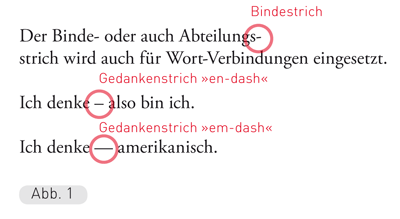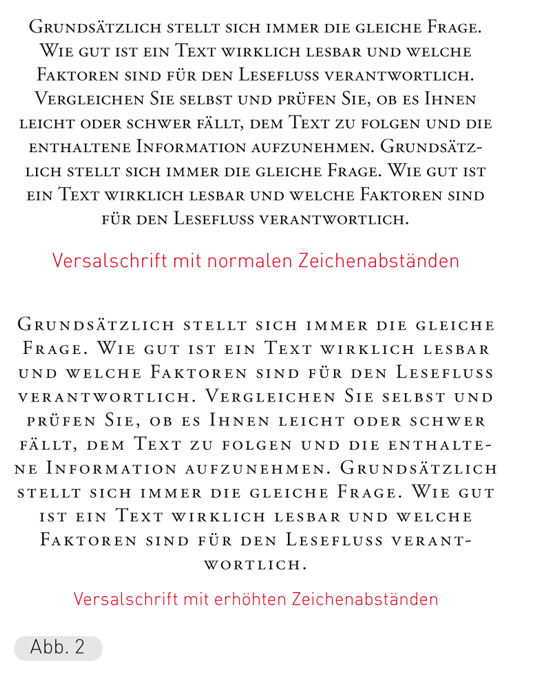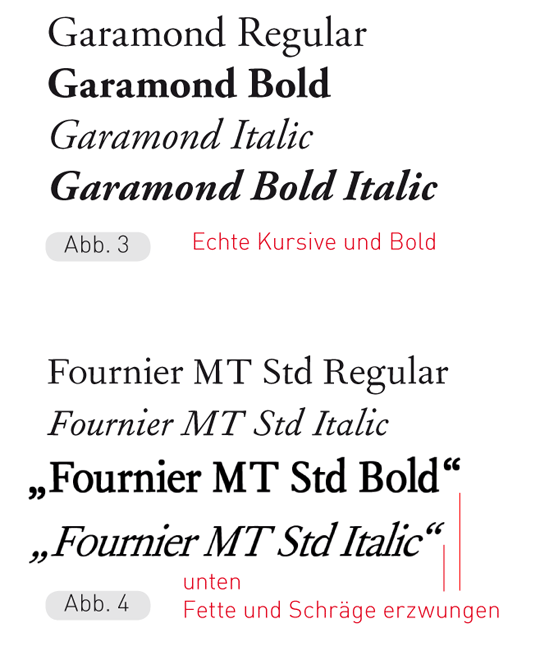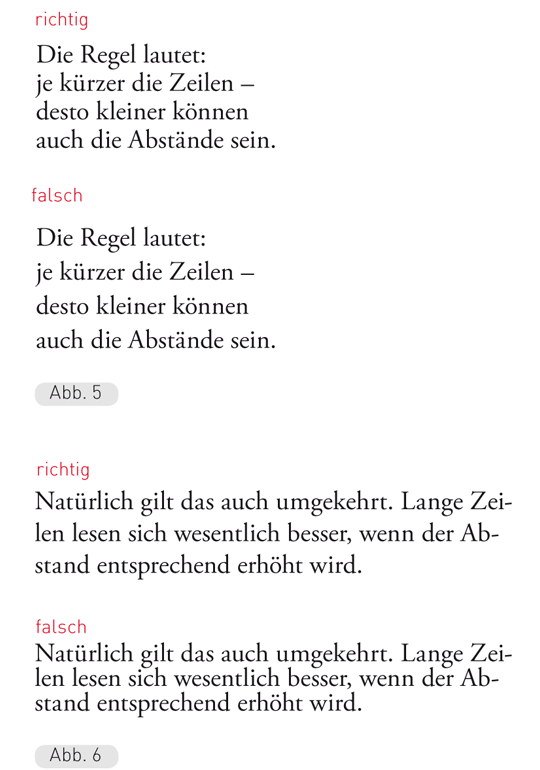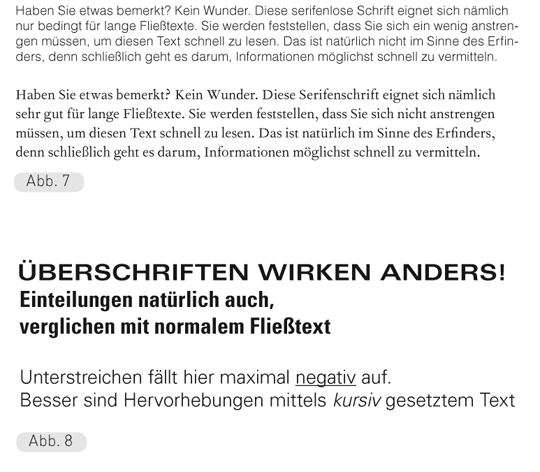
…Einfach einen Text setzen, ein Bild hinzufügen und ein wenig mit den Parametern herumspielen reicht – wie Sie wissen – nämlich nicht aus, um saubere und vor allem effektive Layouts vorweisen zu können. Damit Ihre Arbeiten künftig noch besser und schöner werden, finden Sie hier die wichtigsten Anhaltspunkte in den sogenannten Goldenen Regeln, sprich die wichtigsten Regeln der Typografie. Dabei handelt es sich oft um banale Kleinigkeiten, deren Nichtbeachtung gravierende Auswirkungen auf das Erscheinungsbild Ihrer Arbeit haben können. Sie haben sich im Laufe der Jahrhunderte herausgebildet und begründen sich auf der Leseerfahrung von Millionen und Abermillionen von Lesern. Dennoch sollten die folgenden Ratschläge als solche verstanden werden und Ihnen keinesfalls die Freude am Experimentieren nehmen!
Satzzeichen und Leerzeichen
Jedem Satzzeichen folgt ein Leerzeichen!
Der Fachbegriff für die Satzzeichen (besser: Gliederungszeichen) ist Interpunktionen. Dies ist der allgemeine Sammelbegriff für Punkt, Beistrich (das Komma), Strichpunkt (das Semikolon), Doppelpunkt (das Kolon), Bindestrich (das Divis), Gedankenstrich, Fragezeichen, Ausrufezeichen, runde Klammer (die Parenthese), eckige Klammer, Auslassungszeichen (der Apostroph) und die diversen Anführungszeichen. Das et-Zeichen (&) ist eigentlich eine Ligatur und zählt nicht zu den Interpunktionen. Auch Paragraph, Kreuz und Stern gelten als Zeichen und nicht als Interpunktionen. Jedem Satzzeichen folgt zwar ein Leerzeichen, aber es gibt Ausnahmen wie z.B. bei Bindestrich, Klammer, Apostroph und die Anführungszeichen.
Der Grund, weshalb auf Punkt, Beistrich, Strichpunkt, Doppelpunkt, Gedankenstrich, Frage- und Ausrufungszeichen ein Leerzeichen zu folgen hat, ist ebenso leicht gefunden. Wieder einmal geht es um die Lesbarkeit – um das möglichst rasche Erfassen von Zusammenhängen oder eben Nicht-Zusammenhängen. Der Superstar unter den Zeichen – das Leerzeichen – steht, im Zusammenhang mit einem Satzzeichen, für eine logisch-sinnvolle Pause und gönnt dem Auge den Bruchteil einer Sekunde etwas Erholung.
Gedankenstriche...
Wie Sie bereits wissen, ist Querstrich in der Typografie nicht gleich Querstrich. Immer wieder passiert es, dass anstelle des Gedankenstrichs ein Bindestrich verwendet wird. Diese beiden sind keineswegs gleich. Genauer gesagt wird zwischen drei Arten des Querstriches unterschieden:
- Der Binde- oder Abteilungsstrich ist der kürzeste von den dreien und wird – wie der Name schon sagt – eingesetzt, wenn ein Wort abzuteilen ist beziehungsweise mehrere Wörter miteinander verbunden sein sollen (Abb. 1).
- Der kurze Gedankenstrich oder »endash« ist ein Halbgeviert lang und gilt als der eigentliche – allgemein bekannte Gedankenstrich. Vor und nach dem Gedankenstrich ist unbedingt ein Leerzeichen zu setzen. Dieser Gedankenstrich stellt eine kurze Pause dar oder signalisiert einen Einschub in den Text. Außerdem wird er bei der Angabe von Zeiträumen (von 1860–1996) oder auch als Bindezeichen verwendet, wenn Wegstrecken (Basel–Berlin) angegeben werden. In diesen Fällen allerdings ohne Leerzeichen.
Die Anführungszeichen
Das französische Anführungszeichen wird im Deutschen mit der Spitze zum Wort gesetzt. Die An- und Abführungszeichen stehen ohne Abstand vor beziehungsweise nach dem Wort und symbolisieren in der Regel die wörtliche Rede, während das einfache Anführungszeichen für Begriffe steht – Er sagte: »Das Wort ›Verrat‹ habe ich nie gebraucht«. Ob Sie deutsche oder französische Anführungszeichen verwenden, bleibt Ihnen überlassen. Sie müssen die einmal gewählten Zeichen allerdings im ganzen Dokument beibehalten!
Die Gänsefüßchen oder deutsche Anführungszeichen werden heute kaum noch verwendet, allenfalls bei Frakturschrift, wobei sie am Anfang unten und am Ende oben stehen. Behandelt werden sie wie die anderen Anführungszeichen.
Das Auslassungszeichen (der Apostroph) wird innerhalb eines Wortes ohne Zwischenraum gesetzt. Am Schluss mit etwas weniger Abstand zum nächsten Buchstaben als der übliche Zeichenabstand. Außerdem muss in Zeiten des Desk Top Publishing leider sogar auf den Unterschied zwischen dem Minutenzeichen und einem echten Apostroph hingewiesen werden.
Zeichenabstände
Falls Sie einen Text versal setzen sollten, haben Sie zwei Dinge besonders zu beachten. Einerseits sollten Sie einen kleineren Schriftgrad wählen, um einen optimalen Lesefluß zu gewährleisten, andererseits sollten Sie die Zeichenabstände erhöhen, da die Buchstabenabstände eine Funktion der Buchstabeninnenräume sind.
Je kleiner die Innenräume, desto kleiner auch die Abstände. Je größer die Innenräume, desto größer die Zwischenräume. Da Versalien naturgemäß größere Buchstabeninnenräume besitzen als Kleinbuchstaben, werden bei versal gesetzten Texten die Zeichenabstände logischerweise erhöht (Abb. 2).
Bold und Italic
Sie werden sich nun bestimmt fragen, warum Sie den Gebrauch dieser benutzerfreundlich leicht gemachten Funktionen vermeiden oder überhaupt ganz darauf verzichten sollten. Nun – diese beiden meist verwandten Schriftstile, die Sie mittlerweile in jedem Schreibprogramm vorfinden und derer Sie sich mit einem simplen Hausklick bedienen können, gelten in Typografenkreisen als die übelsten Nebenerscheinungen des Desktop Publishing. Eine Folge des im privaten Bereich immer weiter verbreiteten DTP.
Bei kleineren Schriftfamilien, die vielleicht nur einen Schriftschnitt zu bieten haben, wird – wenn Sie einen der beiden erwähnten Schriftstile anklicken – nämlich folgendes gemacht: Ihr Rechner erzeugt elektronisch einen optisch neuen Schriftschnitt, der in Wahrheit natürlich gar kein Schriftschnitt im herkömmlichen Sinne ist. Es handelt sich dabei bloß um eine elektronisch verbreiterte beziehungsweise schräggestellte Version der ursprünglichen Schrift. Bei größeren Schriftfamilien haben Sie ohnedies zumindest Bold (fette Variante) und Italic (kursive Variante) zur Auswahl. Diese wurden jedoch von einem echten Schriftenhersteller in mühevoller Feinstarbeit unter Beachtung unzähliger Faktoren produziert. Es ist also verständlich, dass die Verwendung von Computer errechneten Schriftstilen in Profikreisen als eklatanter Fehler gilt. Vor allem sind diese Fehler sogar optisch offensichtlich. So werden originale Schriftschnitte durch das Verwenden der Kursiv- oder Fettstellung oft so verändert, dass die Originalschrift völlig verfälscht wird. Bei wirklich großen Schriftfamilien wie z.B. der Garamond haben Sie sogar bis zu zehn (oder auch noch wesentlich mehr) unterschiedliche Schriftschnitte zur Auswahl (Abb. 3 und 4).
Unterstreichen vermeiden
Das Unterstreichen kann mit ruhigem Gewissen als die wohl billigste Form der Hervorhebung bezeichnet werden. Immer wieder werden Sie aber darauf angewiesen sein, innerhalb Ihres Schriftstückes zu differenzieren, d.h. ein Textstück gegenüber einem anderen hervorzuheben. Für diesen Zweck gibt es aber eine Menge wesentlich besserer Lösungen als das Unterstreichen. Die klassische Differenzierung hat ihre Gestalt in der Überschriften-Hierarchie. Traditionell werden hier die dominierenden Versalien übergeordnet gesetzt, der gemischte Satz jedoch untergeordnet. Bei Überschriftengruppen in mehreren Qualitäten gilt es, nicht nur die Schriften und Schriftgrade abzustimmen, sondern auch die Abstände zwischen und unter den Überschriftenzeilen ihrem sachlichen Gewicht und dem Charakter des Schriftstückes entsprechend anzugleichen.
Optimaler Zeilenabstand
Die Wahl des optimalen Zeilenabstands ist für ein Schriftstück von entscheidender Bedeutung. Ist der Zeilenabstand zu gering gewählt, wird dem Leser das Lesen erheblich erschwert. Die einzelnen Zeilen sind nicht mehr als solche zu erkennen, sie konkurrieren förmlich mit den benachbarten Zeilen um die Gunst des Auges. Da ein beträchtlicher Teil der Aufmerksamkeit dem bloßen Trennen und Erkennen der Zeilen gewidmet werden muss, wird einem der Leseprozess somit unerträglich gemacht. Ist der Zeilenabstand hingegen zu groß gewählt, muss der Blick zu große Sprünge zwischen den Zeilen unternehmen. Die Konzentration auf den Inhalt des Textes wird somit erheblich erschwert. In beiden Fällen wird das Ziel der perfekten Zeilenführung – sowohl innerhalb einer einzelnen Zeile als auch die gelungene Überführung zur nächstfolgende Zeile verfehlt.
Lauftexte und Headers
Die Lesbarkeit eines Textes ist von vielen verschiedenen Faktoren abhängig. Aber da auch jedes Textstück ein anderes Ziel verfolgt, muss zum Beispiel beim Gestalten von Headlines einiges berücksichtigt werden. Bei einer Headline gelten nun mal andere Kriterien als beim Fließtext. Während es beim Fließtext ums möglichst rasche, störungsfreie Erfassen des Inhaltes geht, will eine Headline vor allem eines: auffallen! Serifenschriften sind für längere Fließtexte mit Sicherheit die beste Lösung, da sie den Blick aufgrund ihrer Serifen optimal durch die Zeilen führen können. Die Serifen – ein Überbleibsel des An- und Absetzens der Schreibfeder – lassen das Schriftbild ausgewogener und ruhiger erscheinen (Abb. 7).
Für Headlines gelten diese Regeln der Lesbarkeit natürlich nicht, da sie ohnedies in den seltensten Fällen über mehrere Zeilen gehen und somit schnell zu erfassen sind. Headlines sollen vor allem eines sein: plakativ! Und für diesen Zweck sind die modernen serifenlosen (Grotesk-) Schriften wie geschaffen (Abb. 8).